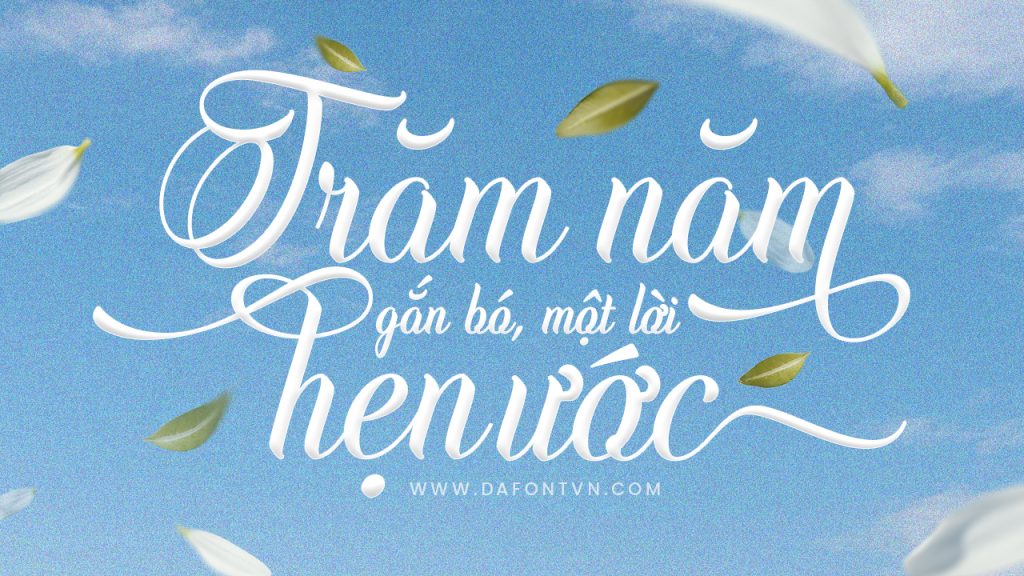
Tổng Hợp Font Chữ Đám Cưới
Font chữ đám cưới là yếu tố quan trọng trong việc tạo nên sự sang trọng và lãng mạn cho thiệp cưới và các tài liệu liên quan đến ngày trọng đại. Với những đường nét mềm mại, tinh tế, các font chữ này thường mang đậm phong cách cổ điển hoặc hiện đại, tùy thuộc vào chủ đề của đám cưới. Việc lựa chọn đúng font chữ đám cưới không chỉ làm nổi bật tên của cô dâu chú rể mà còn giúp tạo nên một tổng thể hài hòa, góp phần thể hiện phong cách và cá tính riêng của cặp đôi.